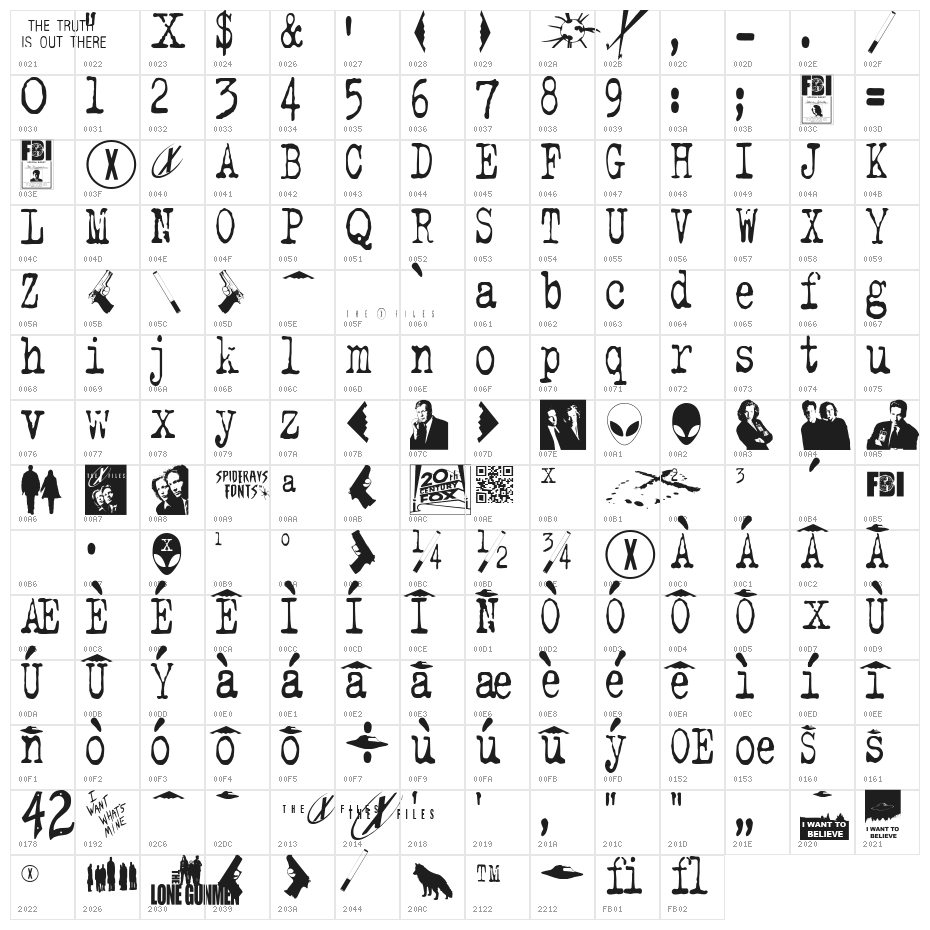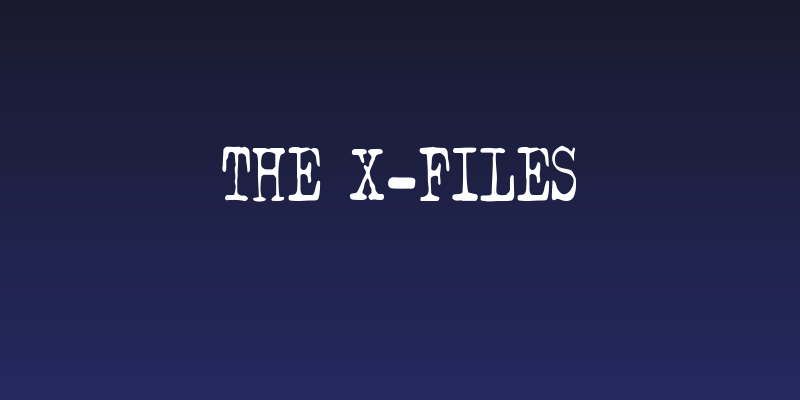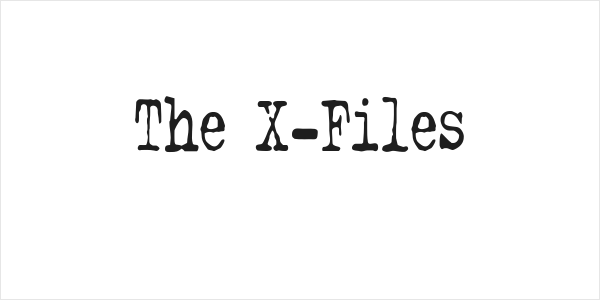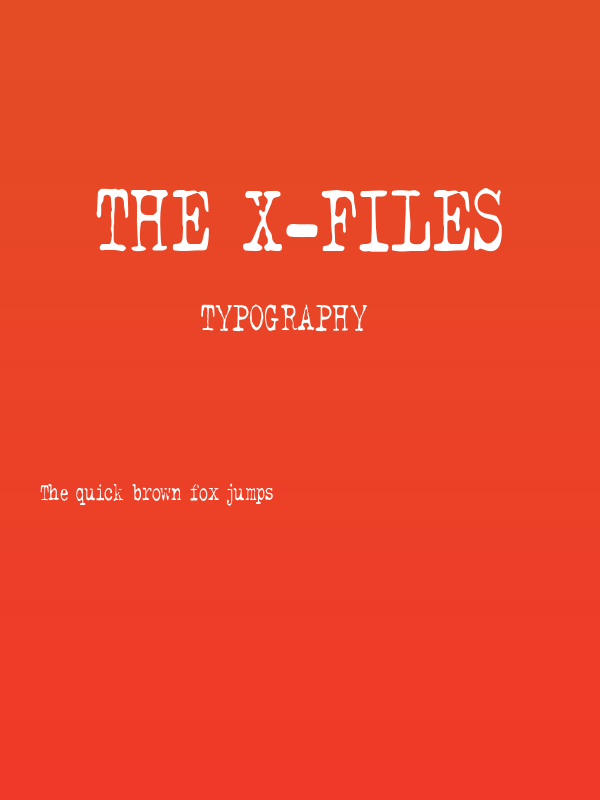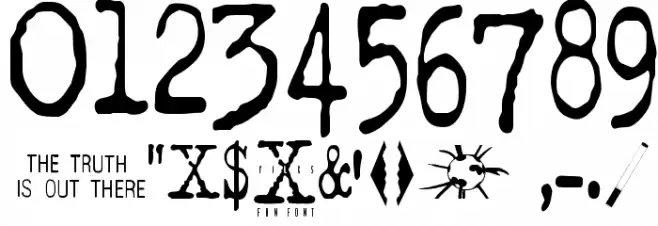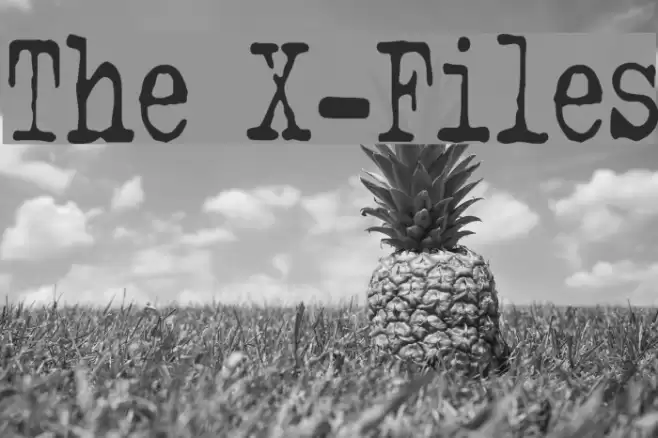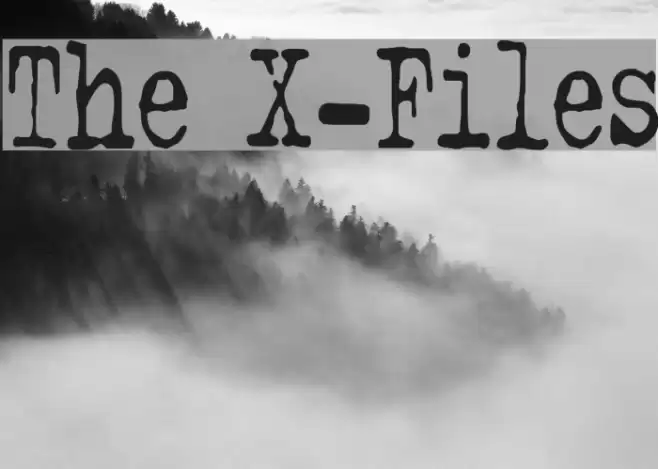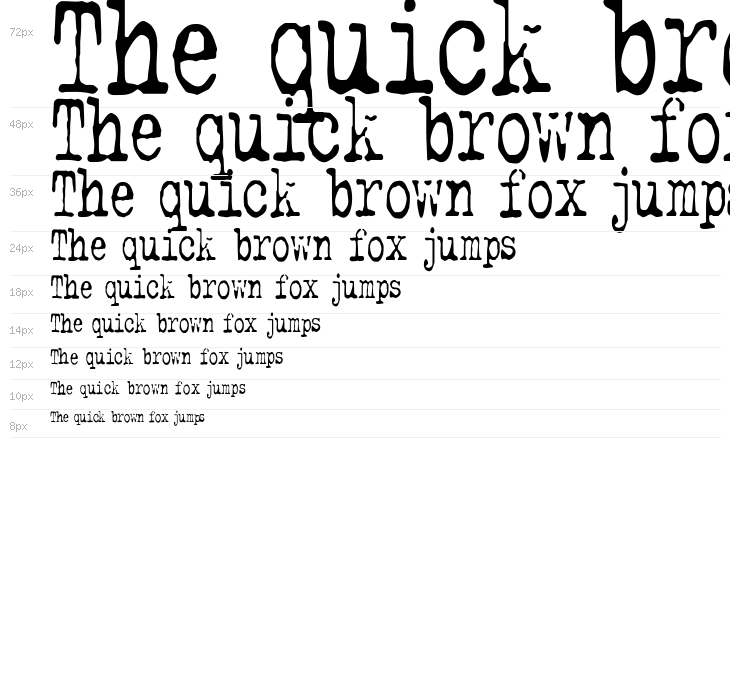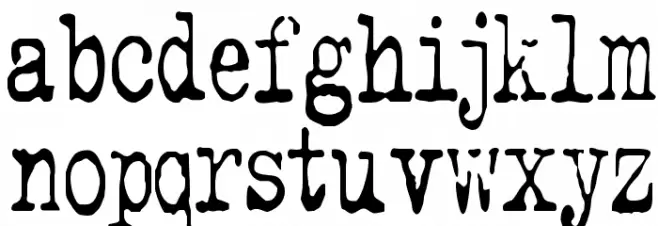
The X-Files Font
| Projets proposés | Ideal for use in horror or mystery-themed posters, book covers, movie titles, and branding that requires a vintage or eerie touch. |